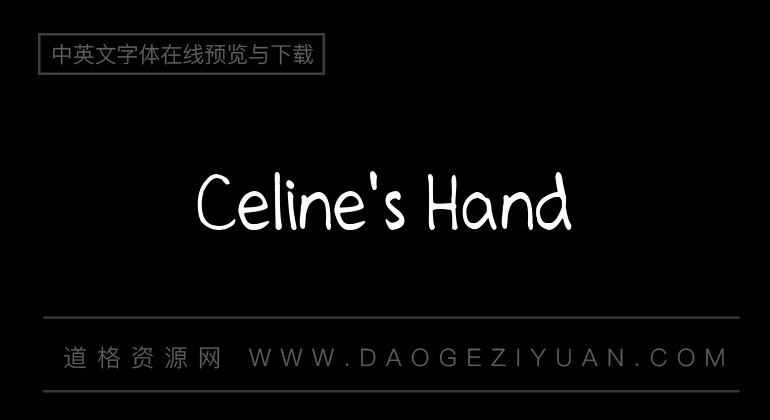
Celine's Hand 是一款手写风格的字体,以其自然、流畅的笔画和精致的形态而受到广泛欢迎。该字体的作者是Celine Simard,是一位加拿大的平面设计师和插画家。 Celine's Hand 字体的特点是具有明显的个性,每个字母都有其独特的特点,让整个字体看起来既有趣又有灵动感。其字母间距离紧凑、线条流畅自然,让人感觉像是手写的而不是印刷的。 这款字体非常适合用于卡片、海报、广告等设计中,能够赋予作品更加亲切、自然的感觉。另外,该字体还提供了不同的字重以及斜体版本,使得设计师可以更灵活地运用它来达到不同的效果。内容介绍
Celine's Hand是一款非常不错的手写艺术字体,具有很好的视觉感,适合于文化类的宣传设计、商业类品牌的广告和产品包装设计以及个性化文字排版等较多场景。